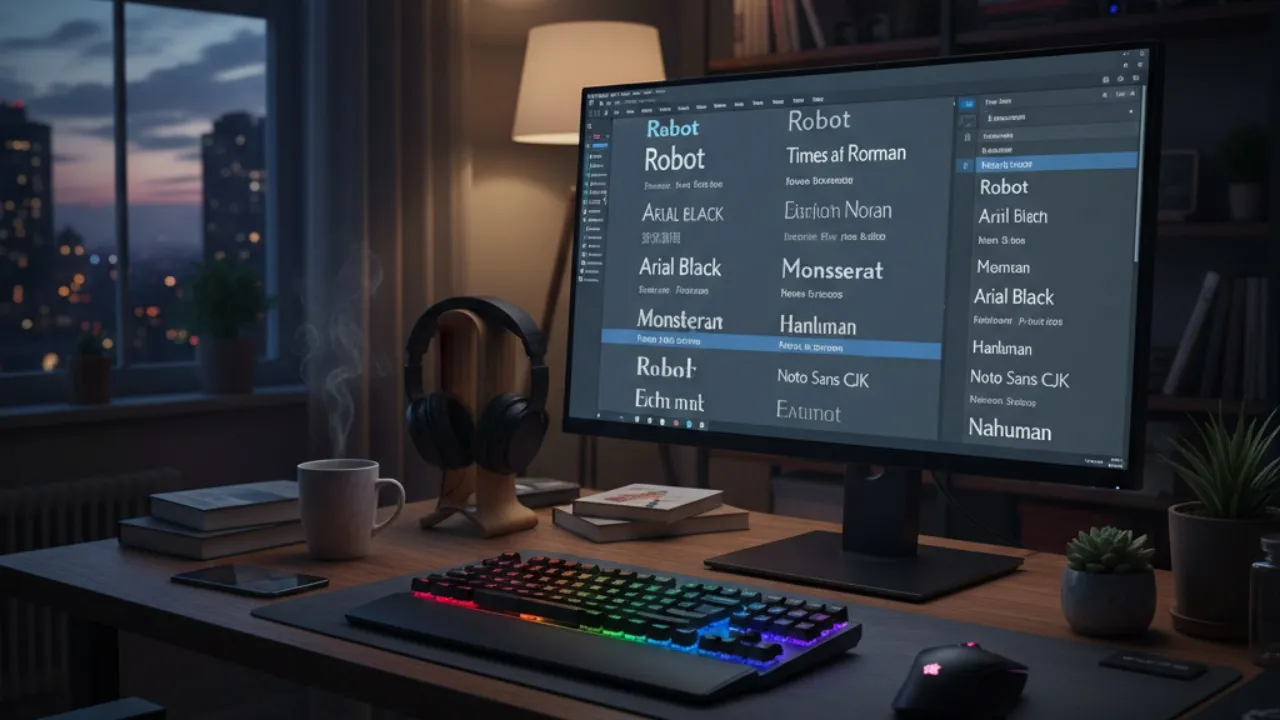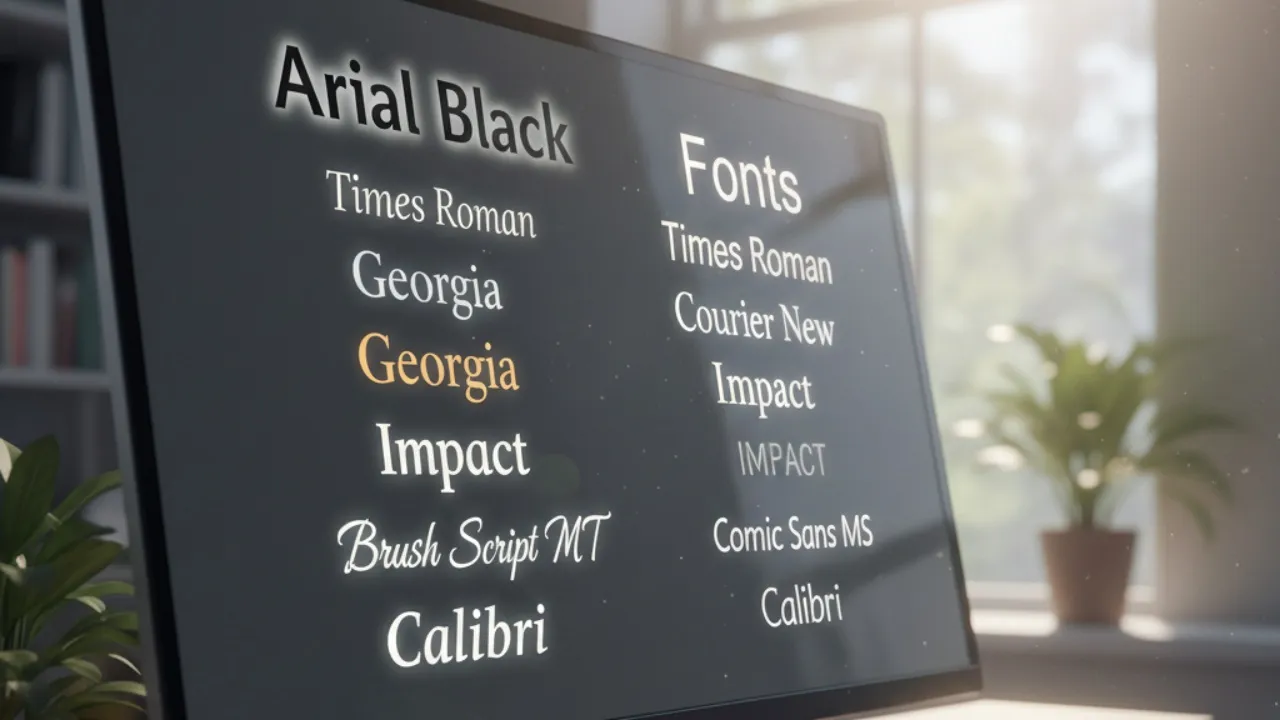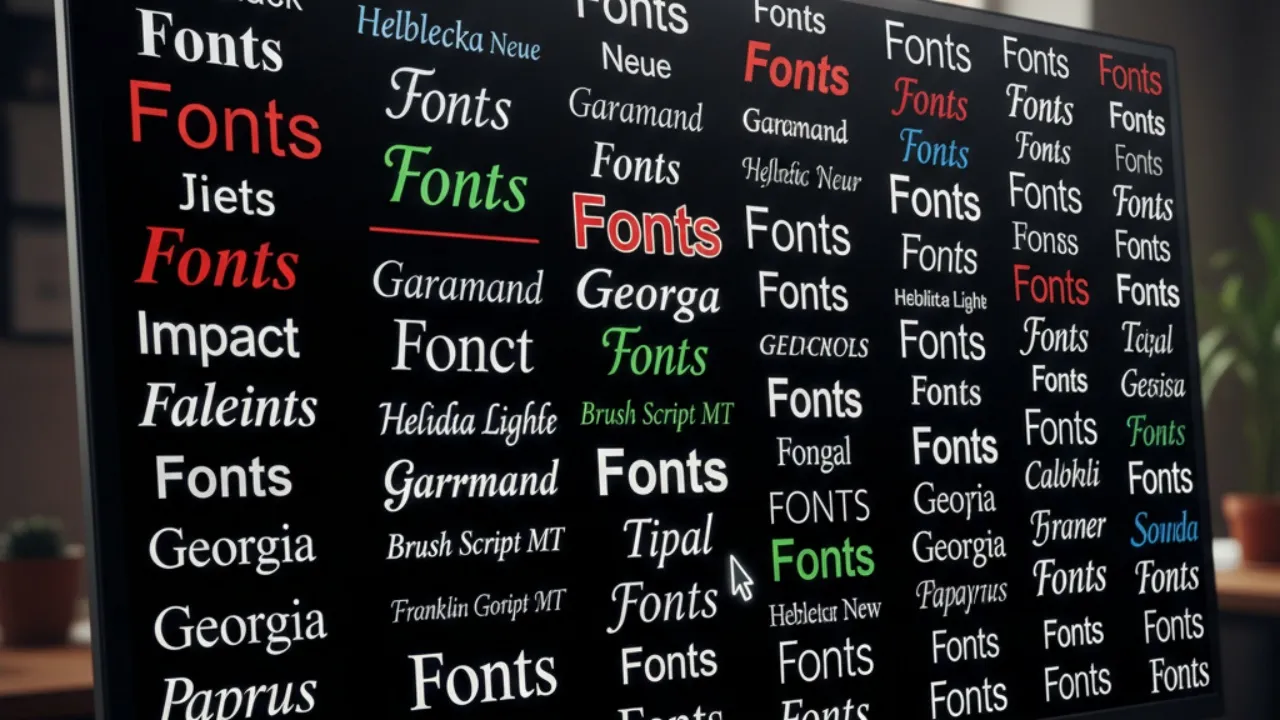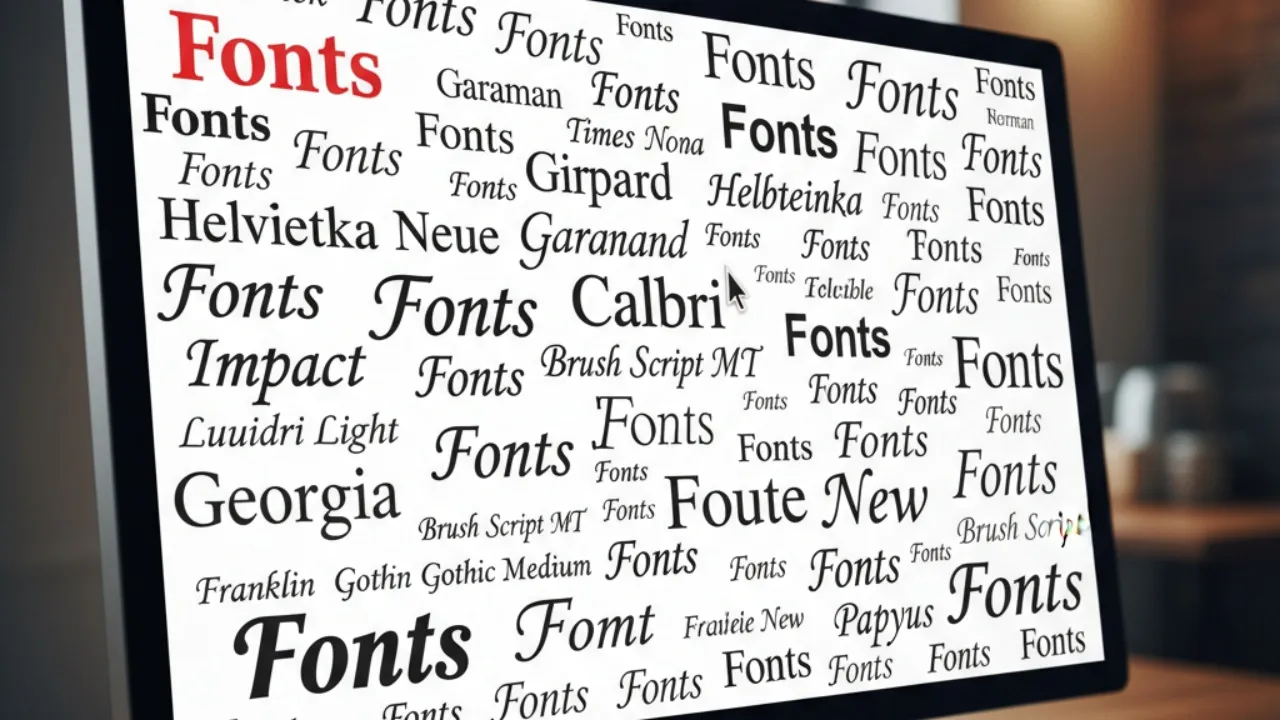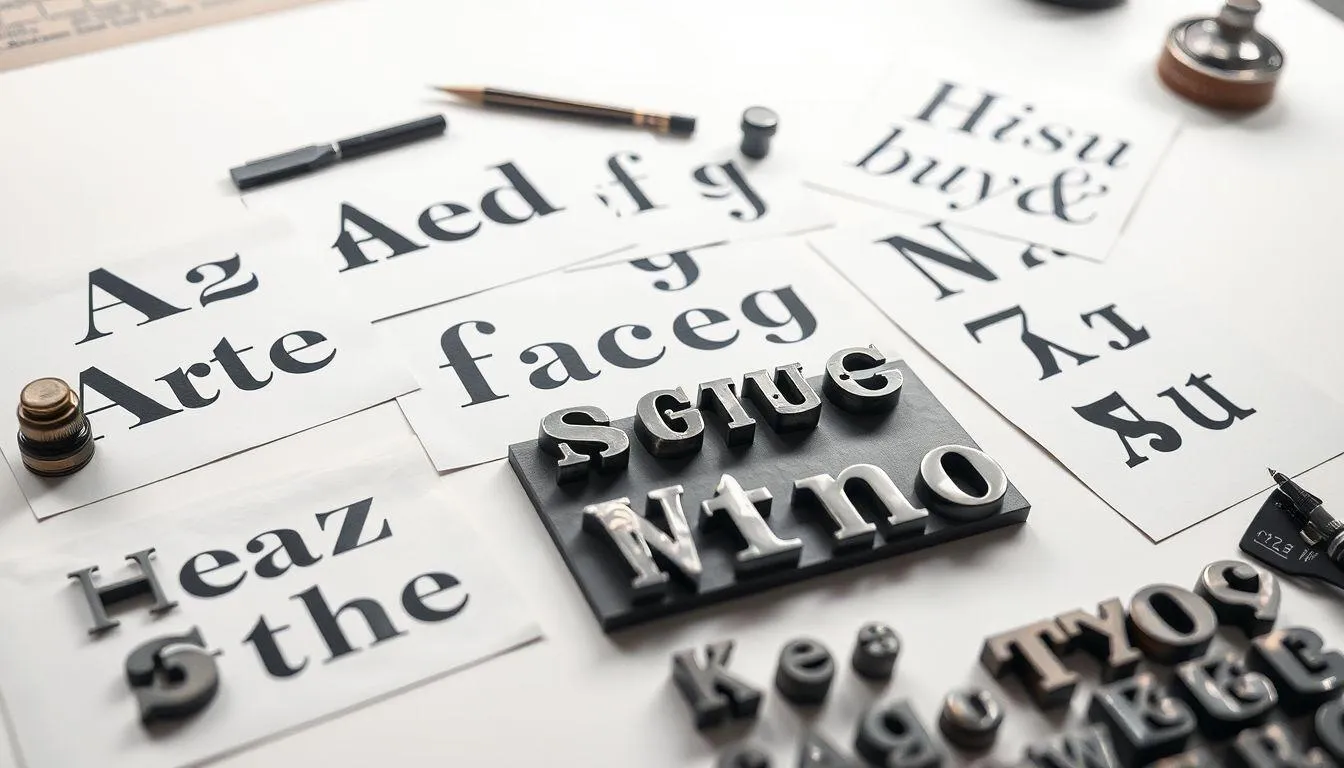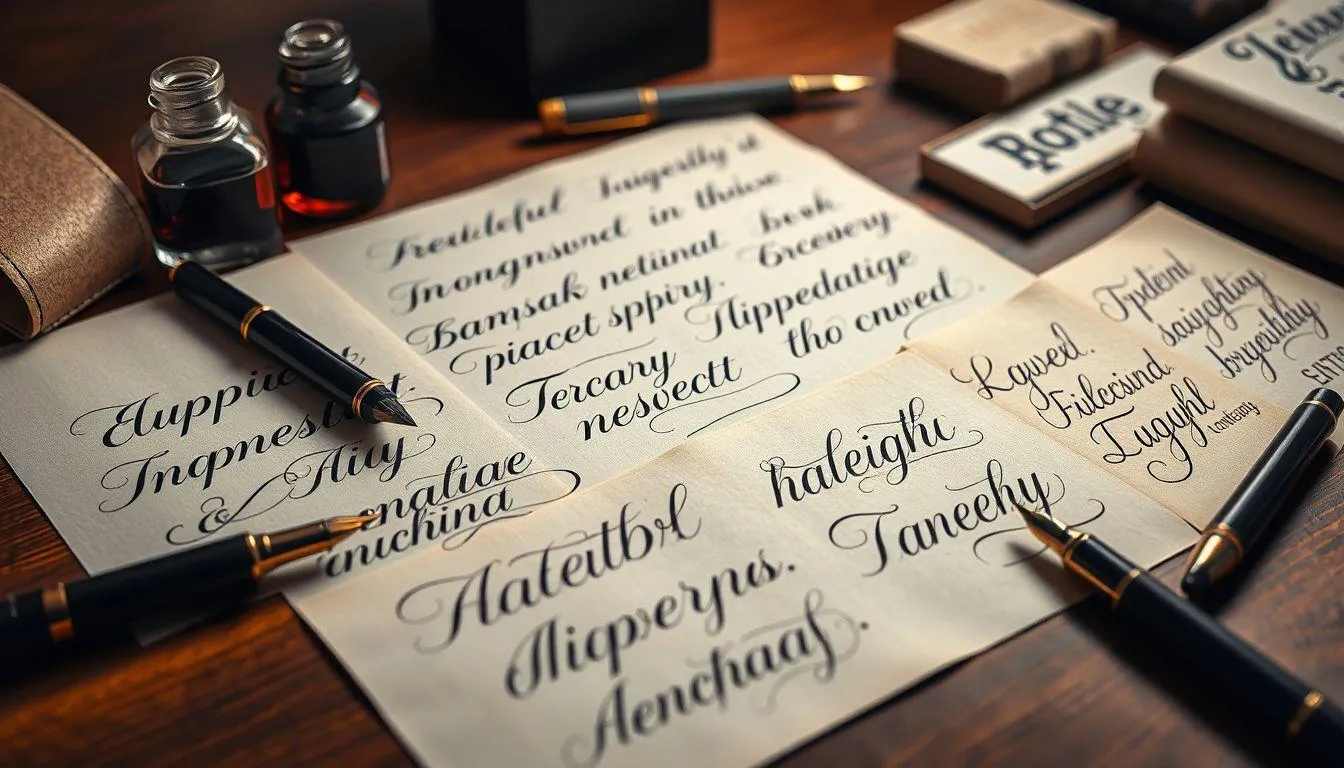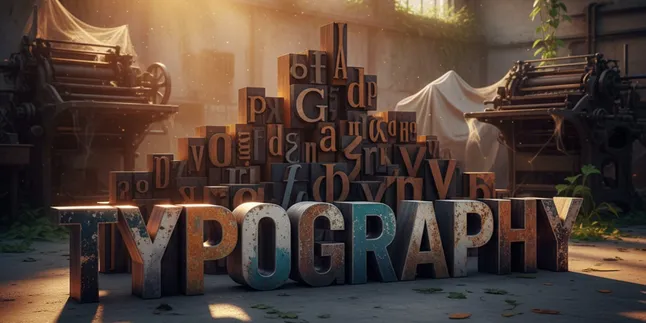
Nama-nama Font: Panduan Lengkap Jenis-jenis Font untuk Desain
Kapanlagi.com - Pemilihan nama nama font yang tepat merupakan salah satu aspek terpenting dalam desain grafis dan tipografi. Setiap jenis font memiliki karakteristik unik yang dapat memengaruhi kesan visual dan keterbacaan suatu karya desain.
Dalam dunia desain modern, terdapat ratusan bahkan ribuan nama nama font yang tersedia untuk berbagai keperluan. Memahami klasifikasi dan karakteristik masing-masing font akan membantu desainer membuat pilihan yang tepat sesuai dengan tujuan komunikasi visual yang diinginkan.
Menurut Typography: A Manual of Design karya Emil Ruder, tipografi bukan hanya tentang keindahan huruf, tetapi juga tentang bagaimana huruf tersebut dapat menyampaikan pesan dengan efektif kepada pembaca.
1. Pengertian dan Klasifikasi Font
Font atau huruf adalah representasi visual dari karakter alfabet, angka, dan simbol yang digunakan dalam komunikasi tertulis. Dalam konteks desain grafis, nama nama font merujuk pada berbagai gaya tipografi yang memiliki karakteristik visual yang berbeda-beda.
Klasifikasi font secara umum dibagi menjadi beberapa kategori utama berdasarkan bentuk dan gaya visualnya. Setiap kategori memiliki ciri khas tersendiri yang membuatnya cocok untuk penggunaan tertentu. Pemahaman yang baik tentang klasifikasi ini akan membantu dalam memilih font yang tepat untuk setiap proyek desain.
Perkembangan teknologi digital telah memperluas variasi nama nama font yang tersedia, mulai dari font klasik yang telah ada sejak era mesin cetak hingga font modern yang dirancang khusus untuk media digital. Setiap font memiliki kepribadian dan karakter yang dapat memengaruhi persepsi pembaca terhadap pesan yang disampaikan.
Menurut penelitian yang dipublikasikan dalam Journal of Applied Psychology, pemilihan font yang tepat dapat meningkatkan tingkat keterbacaan hingga 30% dan memengaruhi persepsi kredibilitas suatu dokumen atau desain.
2. Jenis-jenis Font Serif
Font serif merupakan salah satu kategori nama nama font yang paling klasik dan formal. Ciri khas utama font serif adalah adanya garis kecil atau ornamen pada ujung setiap huruf yang disebut serif. Garis-garis kecil ini membantu mata mengikuti alur teks dengan lebih mudah, sehingga font serif sangat cocok untuk teks panjang seperti buku, artikel, dan dokumen formal.
1. Times New Roman: Font serif yang paling populer dan sering digunakan dalam dokumen akademik dan publikasi resmi.
2. Georgia: Dirancang khusus untuk keterbacaan di layar digital dengan bentuk huruf yang lebih besar.
3. Garamond: Font klasik yang berasal dari abad ke-16 dengan karakteristik elegan dan mudah dibaca.
4. Baskerville: Font transisional yang memadukan elemen klasik dan modern.
5.Cambria: Font modern yang dirancang untuk dokumen bisnis dan presentasi.
6. Bodoni: Font dengan kontras tinggi antara garis tebal dan tipis.
Penggunaan font serif memberikan kesan formal, tradisional, dan dapat dipercaya. Dalam dunia penerbitan, font serif masih menjadi pilihan utama untuk buku dan majalah karena kemudahan membaca dalam teks panjang.
3. Kategori Font Sans Serif
Sans serif, yang berarti "tanpa serif" dalam bahasa Prancis, adalah kategori nama nama font yang tidak memiliki garis tambahan pada ujung huruf. Font ini memberikan kesan modern, bersih, dan minimalis yang sangat cocok untuk media digital dan desain kontemporer.
1. Arial: Font sans serif yang paling umum digunakan dan tersedia di hampir semua sistem operasi.
2. Helvetica: Font Swiss yang menjadi standar dalam desain grafis profesional.
3. Calibri: Font default Microsoft Office dengan desain yang ramah dan modern.
4. Verdana: Dirancang khusus untuk keterbacaan di layar komputer.
5. Futura: Font geometris dengan bentuk yang sangat bersih dan futuristik.
6. Roboto: Font yang dikembangkan Google untuk sistem Android.
Font sans serif sangat populer dalam branding perusahaan teknologi dan startup karena memberikan kesan inovatif dan modern. Banyak perusahaan besar seperti Google, Apple, dan Microsoft menggunakan variasi font sans serif dalam identitas visual mereka.
4. Font Script dan Handwritten
Kategori nama nama font script dan handwritten meniru gaya tulisan tangan dengan berbagai tingkat formalitas. Font script umumnya lebih elegan dan formal, sementara font handwritten memberikan kesan kasual dan personal.
Font script seperti Brush Script MT dan Palace Script MT sering digunakan untuk undangan pernikahan, logo restoran mewah, dan desain yang membutuhkan sentuhan elegan. Karakteristik utama font script adalah huruf-huruf yang saling terhubung dengan lekukan yang halus dan mengalir.
Sementara itu, font handwritten seperti Comic Sans MS, meskipun sering dikritik dalam komunitas desain, tetap memiliki tempatnya untuk materi edukasi anak-anak dan desain yang membutuhkan kesan ramah dan tidak formal. Font handwritten lainnya seperti Amatic SC dan Indie Flower memberikan kesan kreatif dan personal.
Font pairing adalah teknik menggabungkan dua atau lebih font yang saling melengkapi dalam satu desain. Kombinasi yang baik biasanya menggunakan font dengan karakteristik yang kontras namun harmonis, seperti serif untuk heading dan sans serif untuk body text.